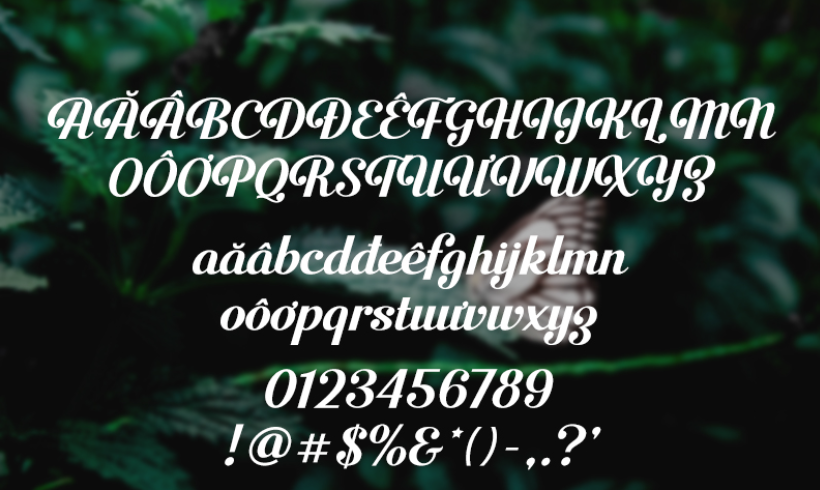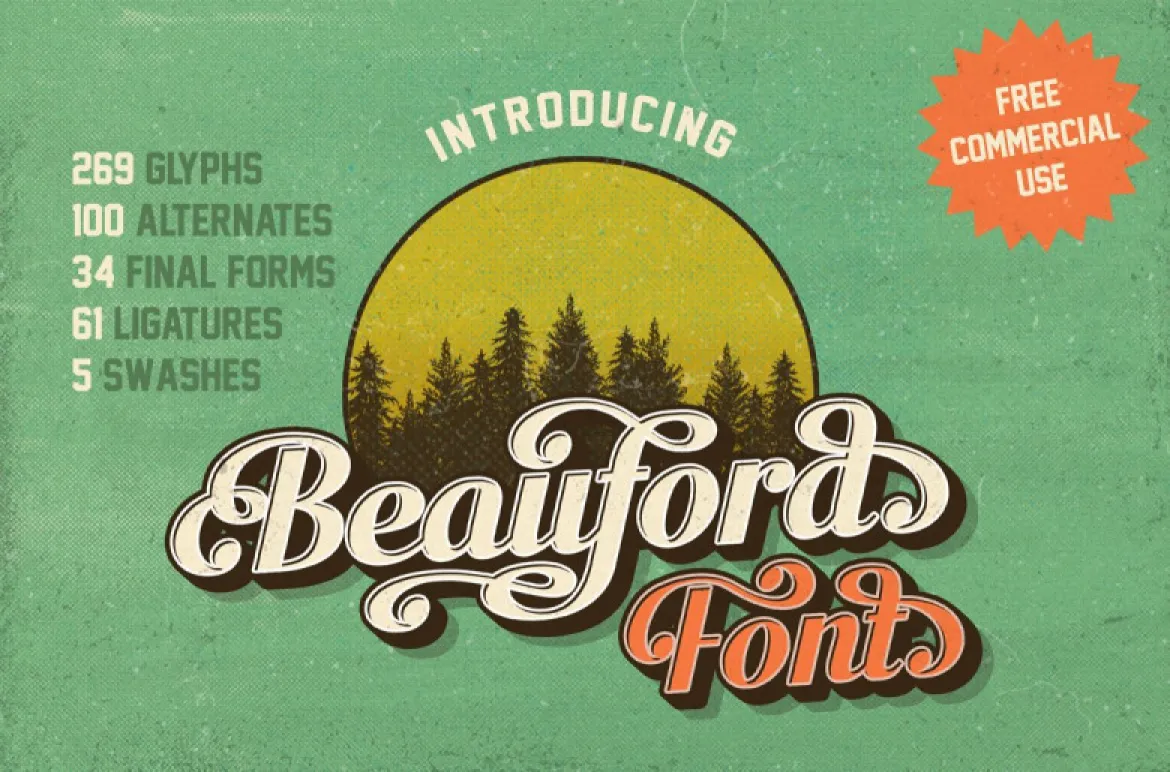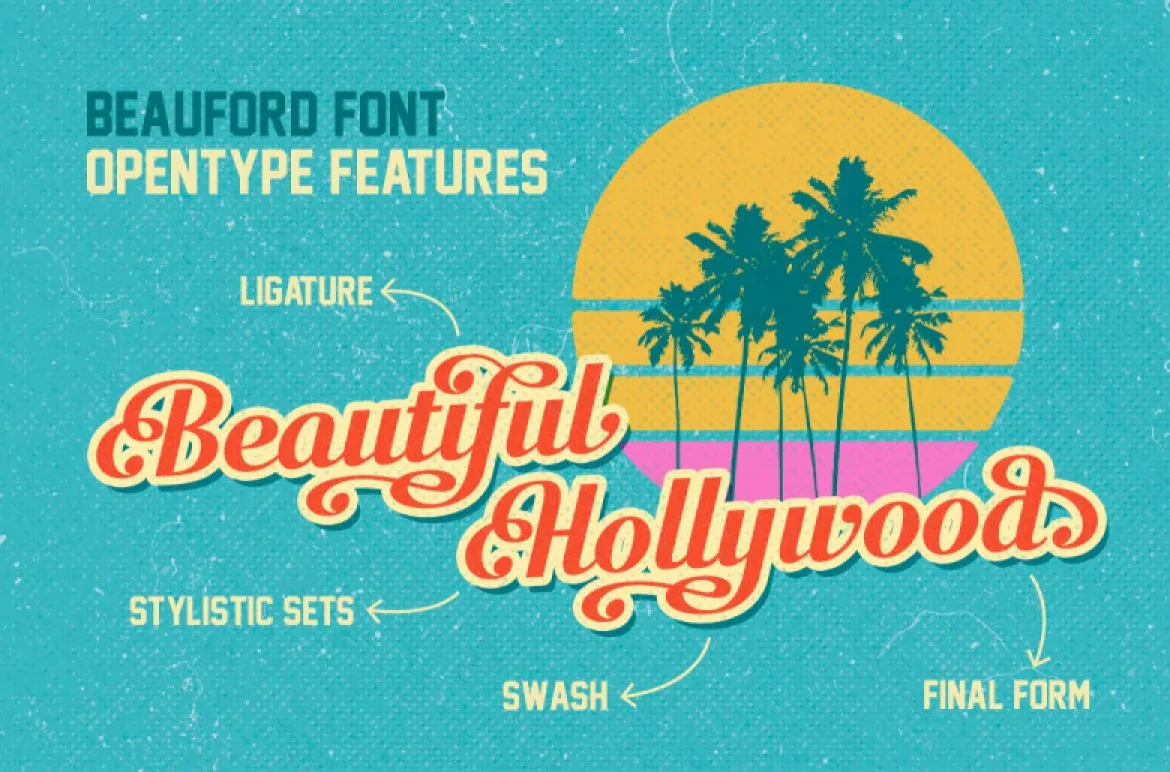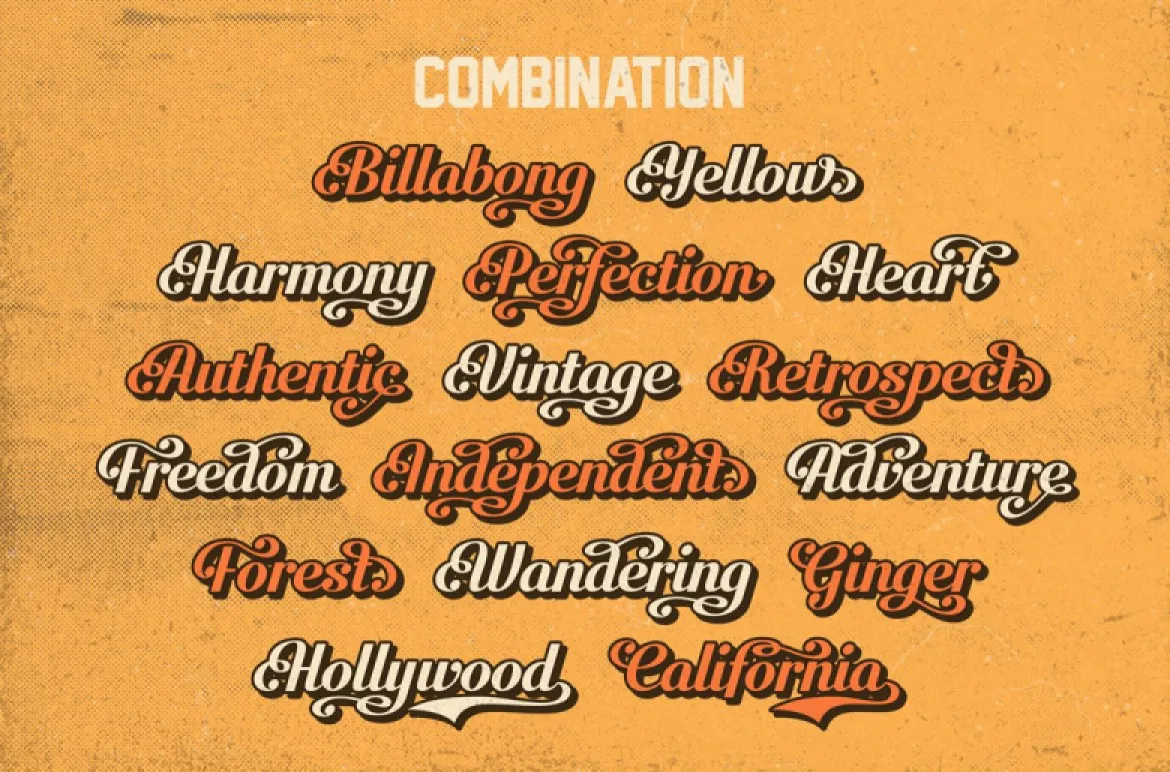
SVN Beauford là bộ phông chữ có chân (Serif) mang đậm phong cách Vintage thời kỳ Victoria (Victorian), nổi bật với những đường nét trang trí sắc sảo, đĩnh đạc và mang chiều sâu cổ kính. Được đội ngũ SVN tinh chỉnh hoàn chỉnh hệ thống dấu tiếng Việt, Beauford là lựa chọn số một cho các thiết kế nhãn chai rượu mạnh, bao bì cà phê hạt hảo hạng, biển hiệu tiệm cắt tóc quý ông và hộp quà tặng mang phong cách di sản. Doozypack.vn chia sẻ link download font SVN Beauford Việt hóa chuẩn kỹ thuật, giúp bạn sở hữu phông chữ đẳng cấp mà không lo gặp bất kỳ lỗi hiển thị dấu thanh nào khi thiết kế in ấn.
Đặc điểm thẩm mỹ độc đáo của bộ font SVN Beauford
Beauford tái hiện trọn vẹn tinh thần đồ họa của thế kỷ 19, nơi mỗi mặt chữ đều được trau chuốt tỉ mỉ như những tác phẩm điêu khắc kim loại cổ điển.
Phong cách Victorian cổ điển và quý phái
Đặc trưng lớn nhất của SVN Beauford là cấu trúc chữ có chân dạng khối vuông dứt khoát kết hợp cùng các góc nhọn trang trí (spurs) ở thân chữ. Thiết kế này gợi liên tưởng đến những bảng hiệu vẽ tay của các cửa hiệu lâu đời tại châu Âu hay nhãn mác của các hầm rượu danh tiếng. Khi sử dụng phông chữ này làm tiêu đề trên bao bì, thương hiệu của bạn sẽ ngay lập tức toát lên vẻ chững chạc, uy tín và sự cam kết về chất lượng gia truyền.
Chi tiết chân chữ và đường nét trang trí dứt khoát
Các ký tự của font SVN Beauford sở hữu độ tương phản nét thanh đậm vừa phải, các nét dọc dày dặn tạo nên sự vững chãi tuyệt đối. Tỷ lệ chữ được căn chỉnh cân đối, giúp các khối văn bản tiêu đề hiển thị mạnh mẽ, uy lực và rất dễ nhận diện từ xa trên kệ hàng, cực kỳ ăn ý với các dòng sản phẩm nam tính và cao cấp.
03 Ưu điểm nổi bật của bản font SVN Beauford Việt hóa
Khi ứng dụng các phông chữ cổ điển vào thị trường trong nước, sự chỉn chu về dấu câu là yếu tố quyết định đến tính chuyên nghiệp của bản thiết kế:
- Khắc phục triệt để lỗi dấu tiếng Việt: Phiên bản font SVN Beauford Việt hóa đã được đội ngũ SVN trau chuốt thủ công từng dấu câu. Các dấu sắc, huyền, hỏi, ngã, nặng được vẽ với độ dày và góc cạnh hoàn toàn ăn khớp cùng thân chữ gốc, không tạo cảm giác chắp vá hay làm biến dạng cấu trúc chữ.
- Bảo đảm tính đồng nhất thương hiệu: Việc tải font Việt hóa SVN Beauford chuẩn giúp bạn tự tin dàn trang tiêu đề tiếng Việt mà không lo hiện tượng lỗi ô vuông hay nhảy về font hệ thống khô khan.
03 Ứng dụng thực tế của font SVN Beauford trong sản xuất bao bì
Sự lịch lãm và quý phái của Beauford mang lại hiệu ứng thị giác đắt giá trên các dòng sản phẩm bao bì thực tế do Doozypack.vn sản xuất:
- Nhãn dán chai Rượu mạnh (Whiskey, Rum): Tiêu đề thương hiệu in bằng font Beauford kết hợp kỹ thuật ép kim nhũ đồng trên giấy decal kháng nước tạo nên diện mạo vô cùng đẳng cấp và sang trọng.
- Bao bì Cà phê hạt & Hộp Socola đen: Nét chữ cổ điển kết hợp hoàn hảo cùng chất liệu giấy Kraft nâu hoặc giấy mỹ thuật nhám, tạo nên phong cách mộc mạc nhưng đậm đà phong vị châu Âu.
- Túi giấy thời trang cổ điển & Barbershop: Dùng cho tên cửa hàng in trên nền túi tối màu tạo phong cách lịch lãm, nam tính và tạo dựng niềm tin bền vững.
03 Lưu ý kỹ thuật khi in ấn với phông chữ Vintage nhiều chi tiết Beauford
Việc sản xuất bao bì thực tế sử dụng các phông chữ có chân sắc nét như Beauford đòi hỏi sự am hiểu kỹ thuật chuyên sâu tại xưởng in Doozypack.vn:
- Kiểm soát độ dày nét chân chữ khi ép kim: Các góc chân chữ của font chữ này khá mảnh. Khi gia công ép kim vàng (Hot Stamping), designer nên đảm bảo nét chữ có độ dày tối thiểu 0.15mm để nhũ bám dính sắc nét, không bị đứt đoạn.
- Lựa chọn chất liệu giấy phù hợp: Beauford phát huy vẻ đẹp tối đa trên giấy Kraft mộc hoặc giấy Ivory cán màng mờ. Bề mặt giấy không quá bóng sẽ tôn vinh trọn vẹn chất cổ điển và chiều sâu của nét chữ.